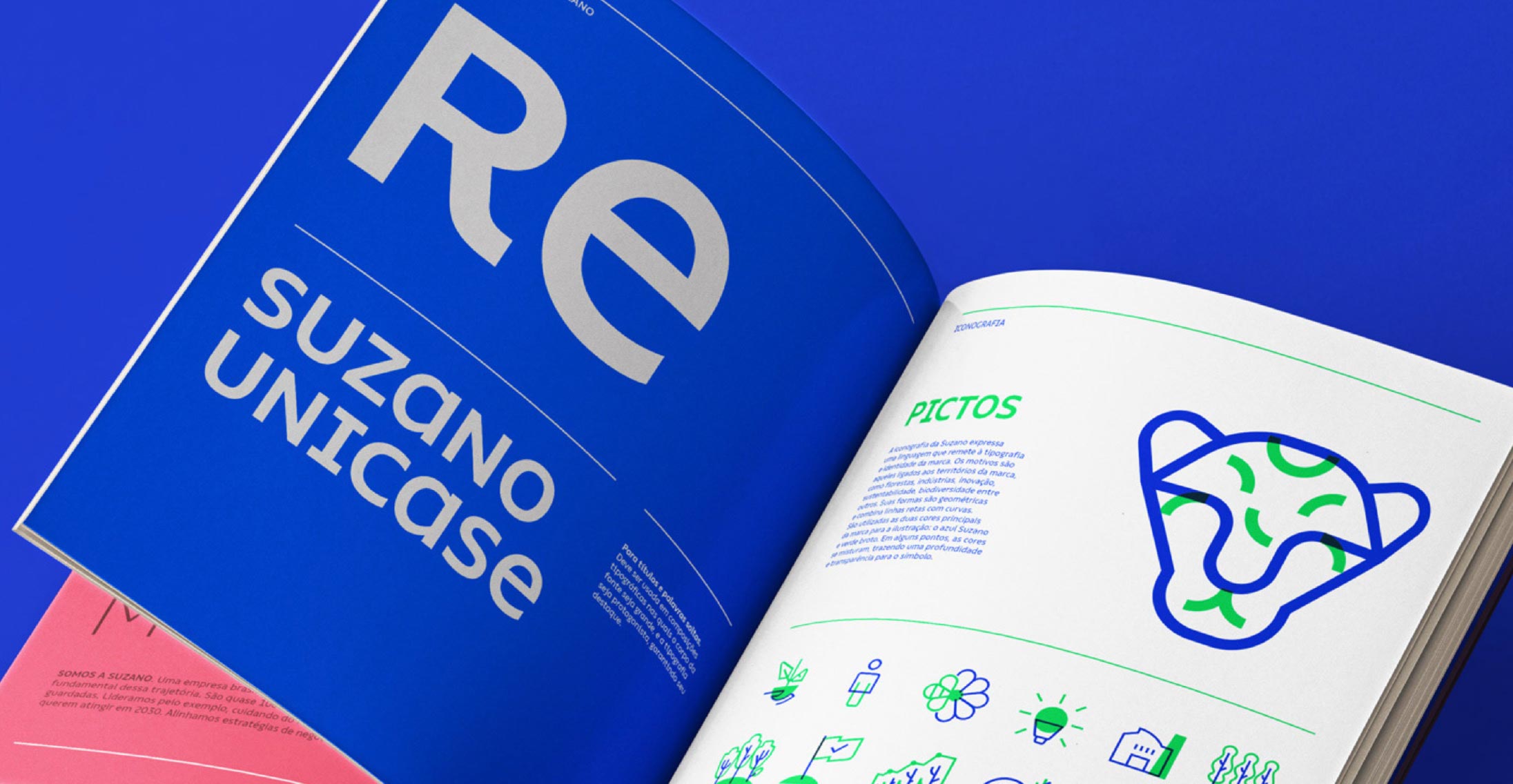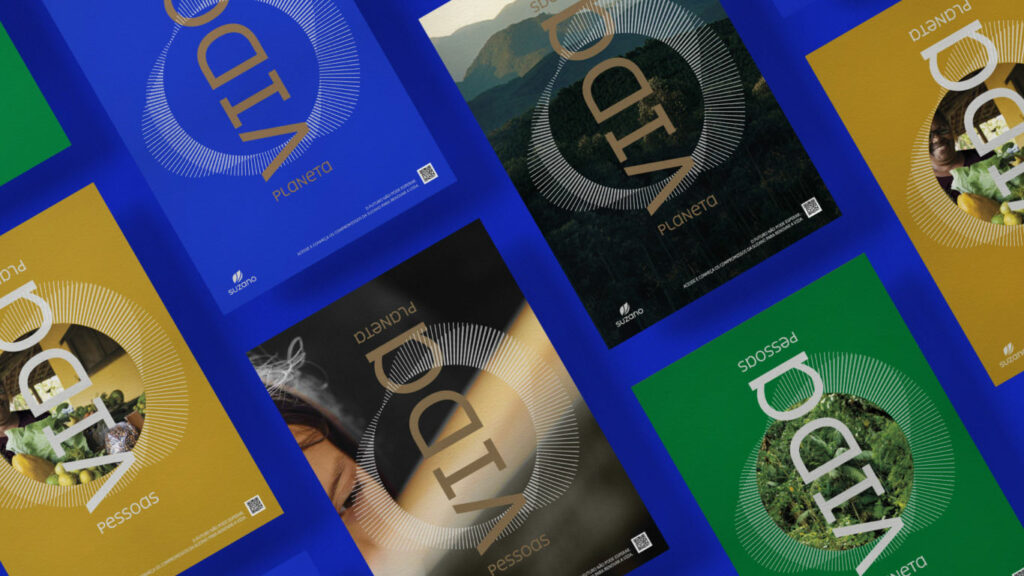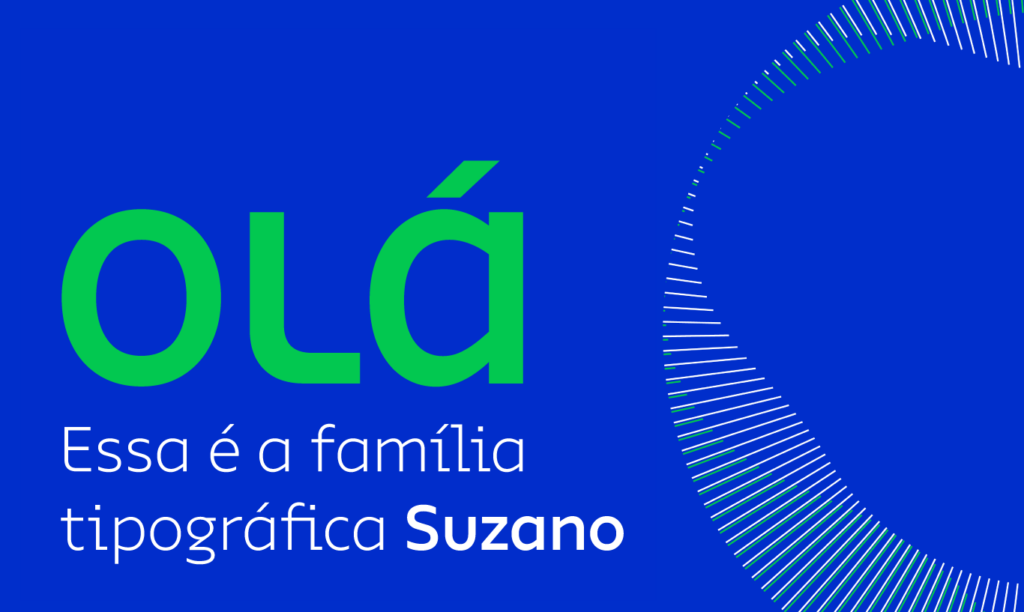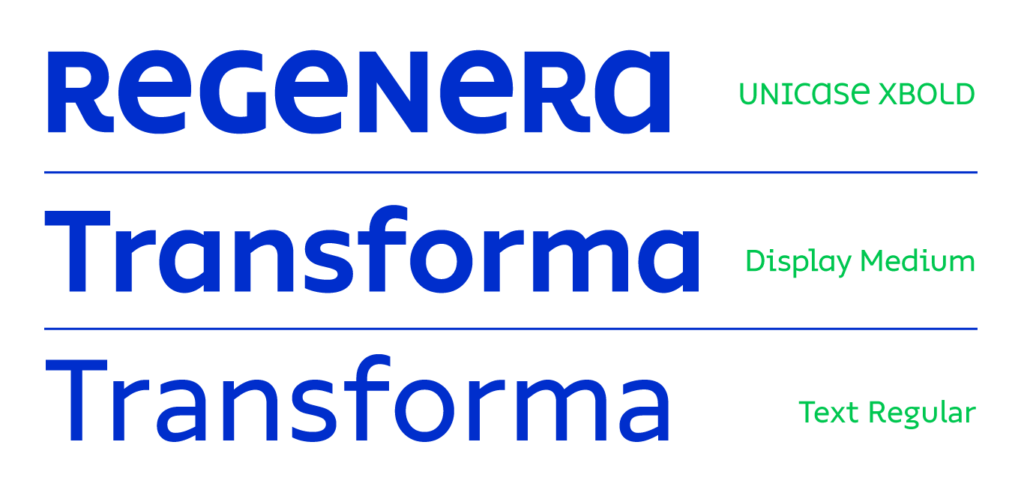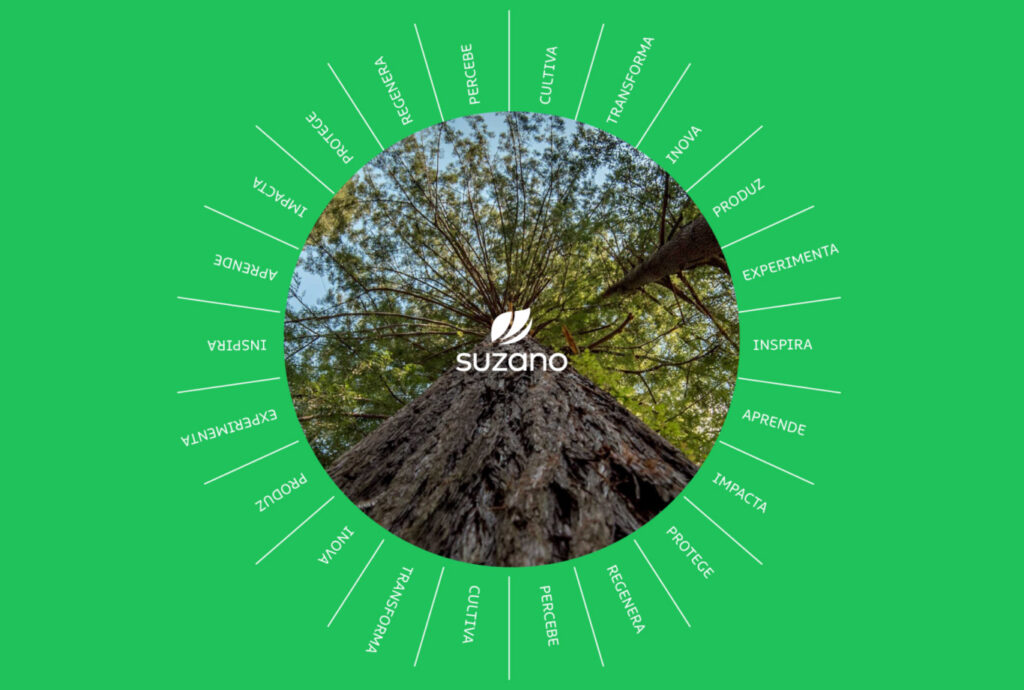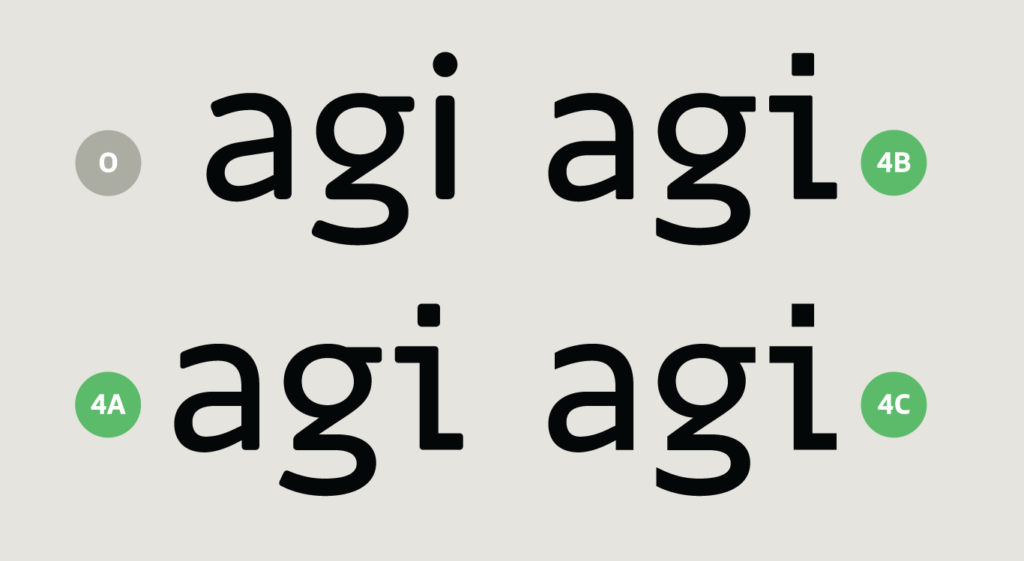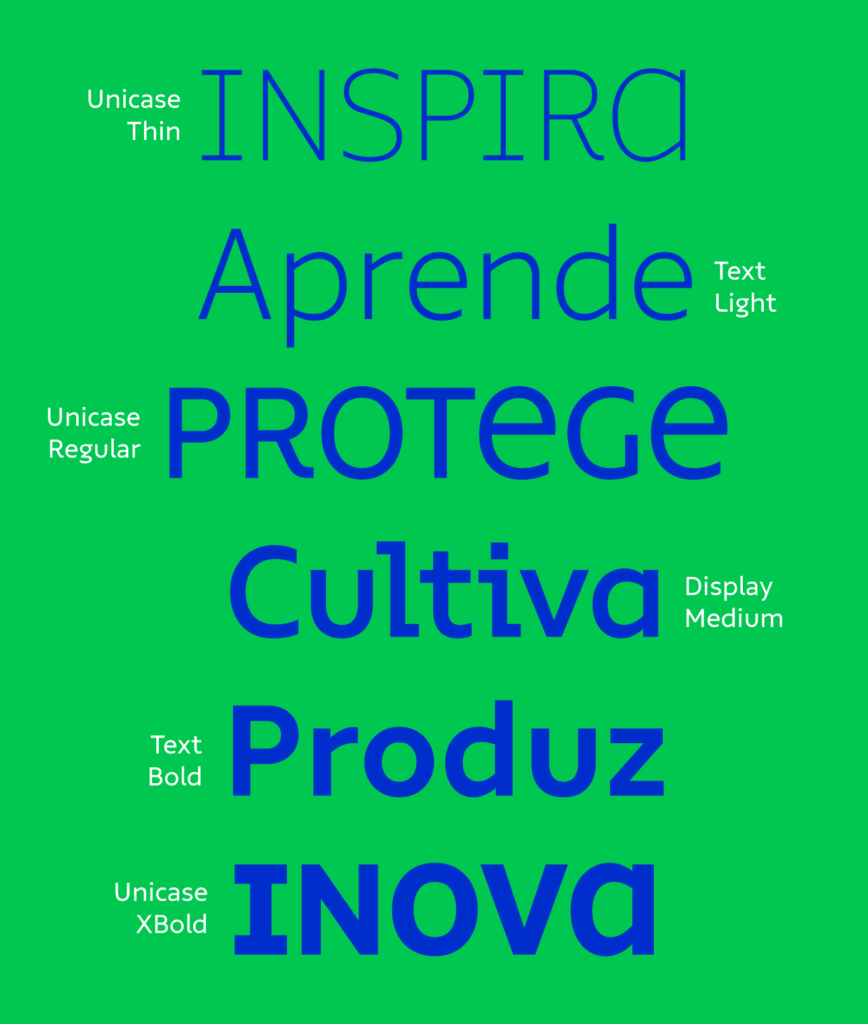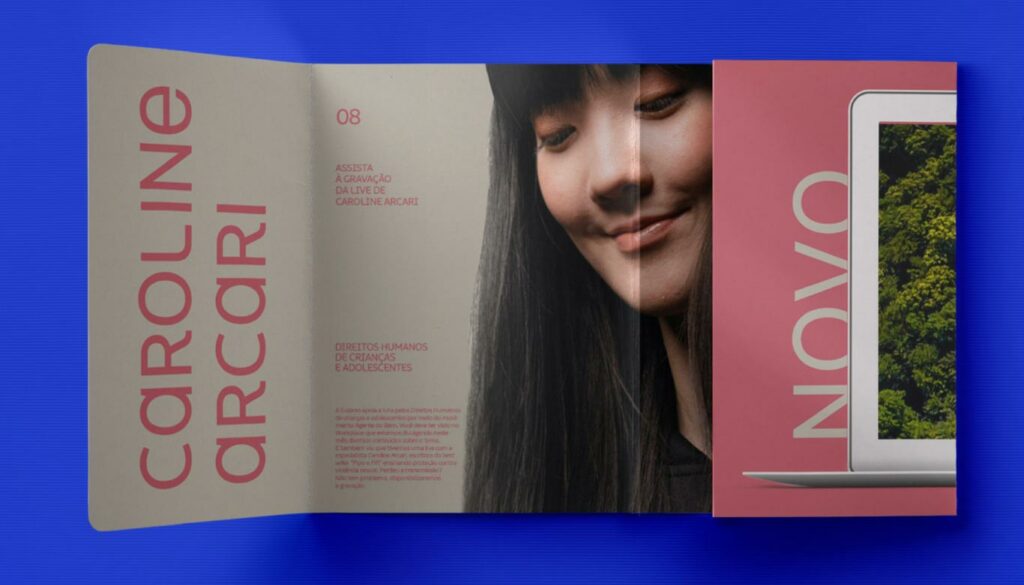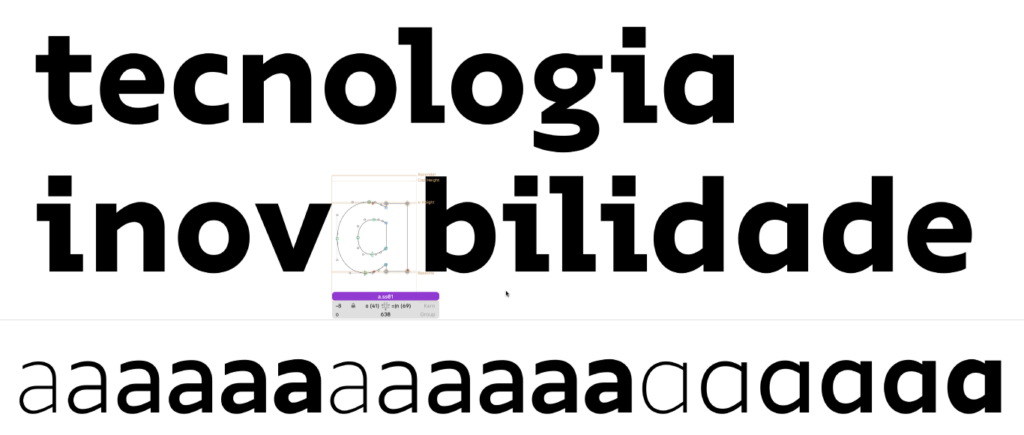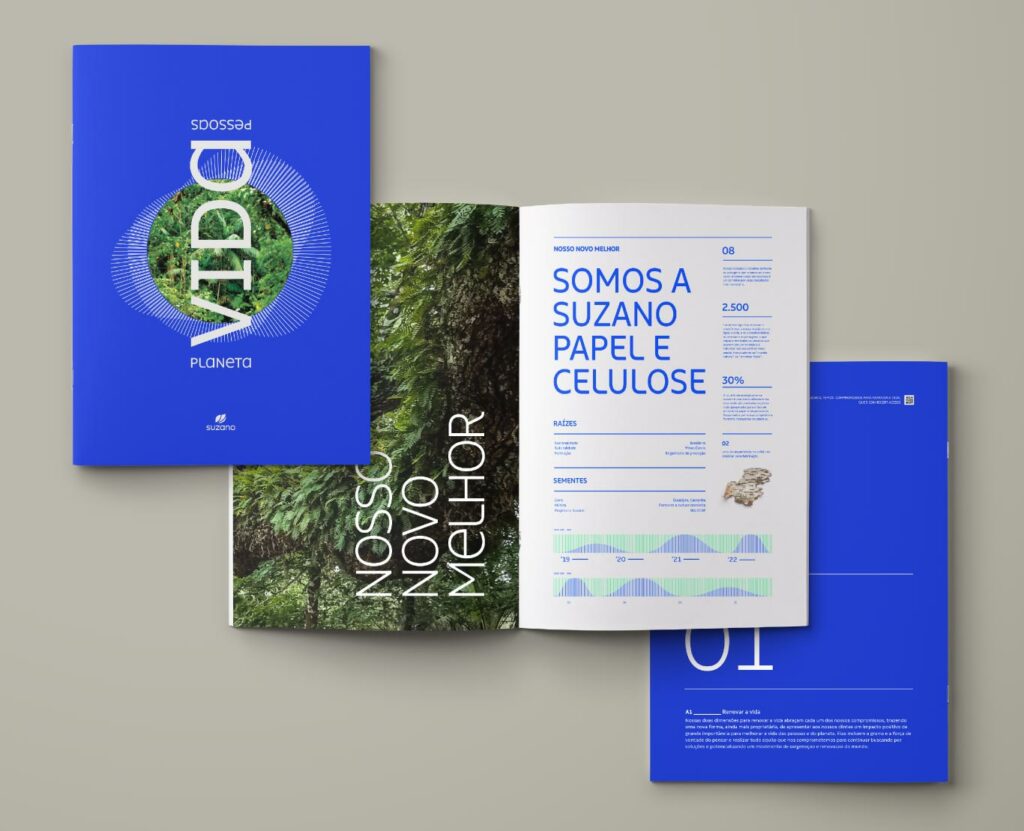
Suzano: um ciclo vivo
O compromisso com a evolução constante para a Suzano vai muito além das palavras, está presente até em suas letras. Há 4 anos, a Fabio Haag Type projetou uma tipografia sob medida com o objetivo de tornar a marca Suzano mais amigável ao grande público. Menos B2B, mais B2C. Agora, junto com a Tátil Design, reinventamos nosso próprio trabalho mirando longe, juntos, no futuro.
A Tátil encontrou e consolidou o lugar de potência da Suzano na Inovabilidade — conceito que une inovação e sustentabilidade e que permeia todas as ações da Suzano. Surge uma nova expressão, representada pelo ciclo vivo, para transmitir constante evolução e dar protagonismo à marca-mãe, e na definição de movimentos futuros que garantam uma troca de valores no ecossistema. O resultado foi a amplificação da história da Suzano para levar ao mundo tudo que a marca tem realizado há quase 100 anos para criar soluções para as pessoas e o planeta.
A Tátil ampliou o uso da tipografia em busca de uma voz mais madura e protagonista, trazendo mais flexibilidade e uma maior conexão com o novo momento da marca. A construção das letras tem a mesma estrutura da anterior, preservando sua essência, mas agora os cantos arredondados deram lugar à precisão com terminações retas. Serifas quadradas em algumas letras da versão Display (como ‘i’, ‘j’ e ‘l’) injetam tecnologia na voz da marca e aumentam a acessibilidade, facilitando o reconhecimento destas letras individuais. Uma variação unicase, com formas maiúsculas e minúsculas na mesma altura, não deixa dúvidas de que a Suzano está em constante movimento, num ciclo vivo.